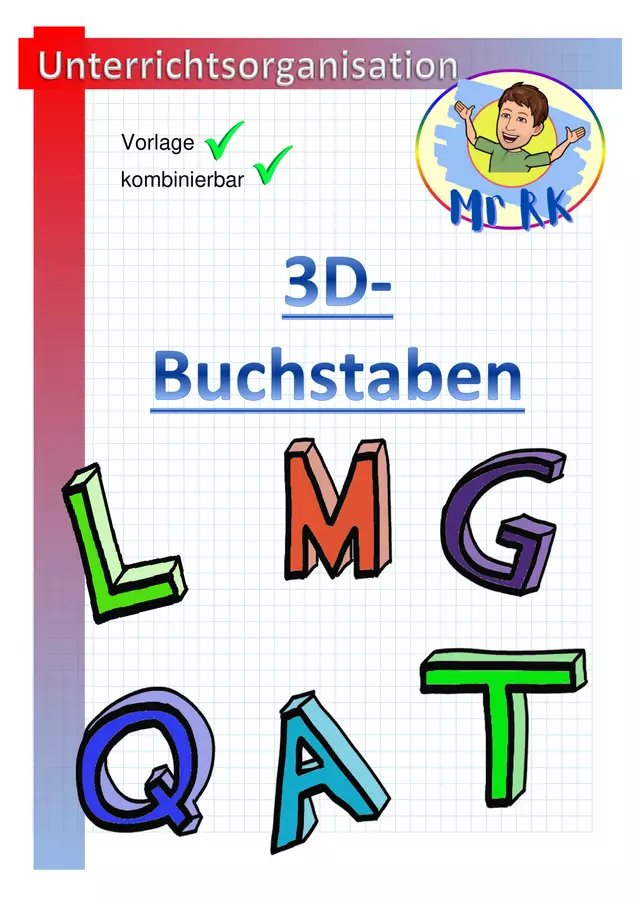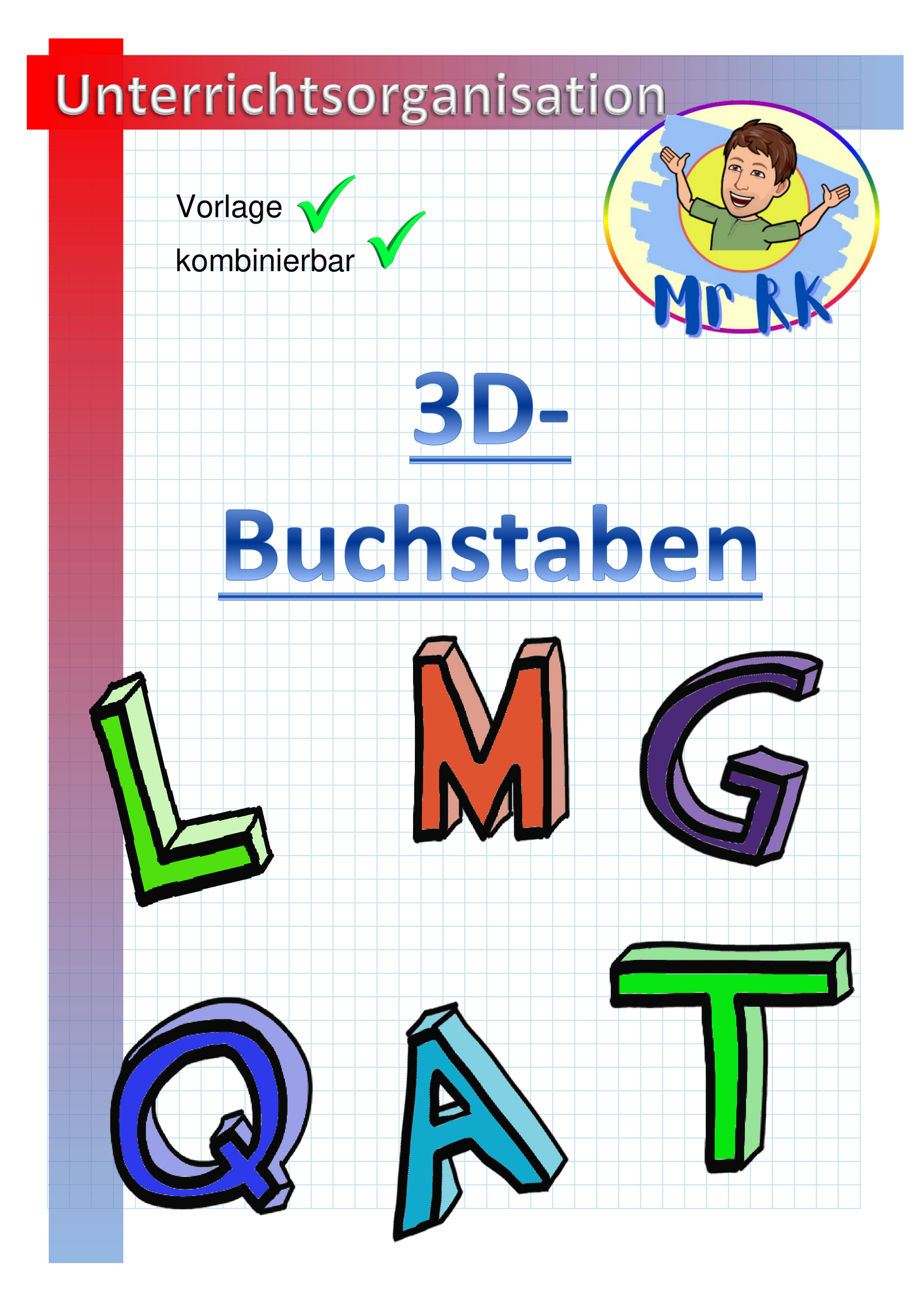
hier habe ich für euch mein selbst gezeichnetes 3D- Alphabet.
Die Buchstaben sind in Form von Bildern und können frei kombiniert, vergrößert und verkleinert werden.
3D Schriftart komplettes Alphabet